2 Open-Source-Schriftfamilien von GitHub
Die Plattform GitHub präsentiert jetzt zwei variable Open-Source-Schriftfamilien, die in Zusammenarbeit mit dem Design-Studio Degarism entstanden sind. »Mona Sans« und »Hubot Sans« sollen sich gegenseitig ergänzen.
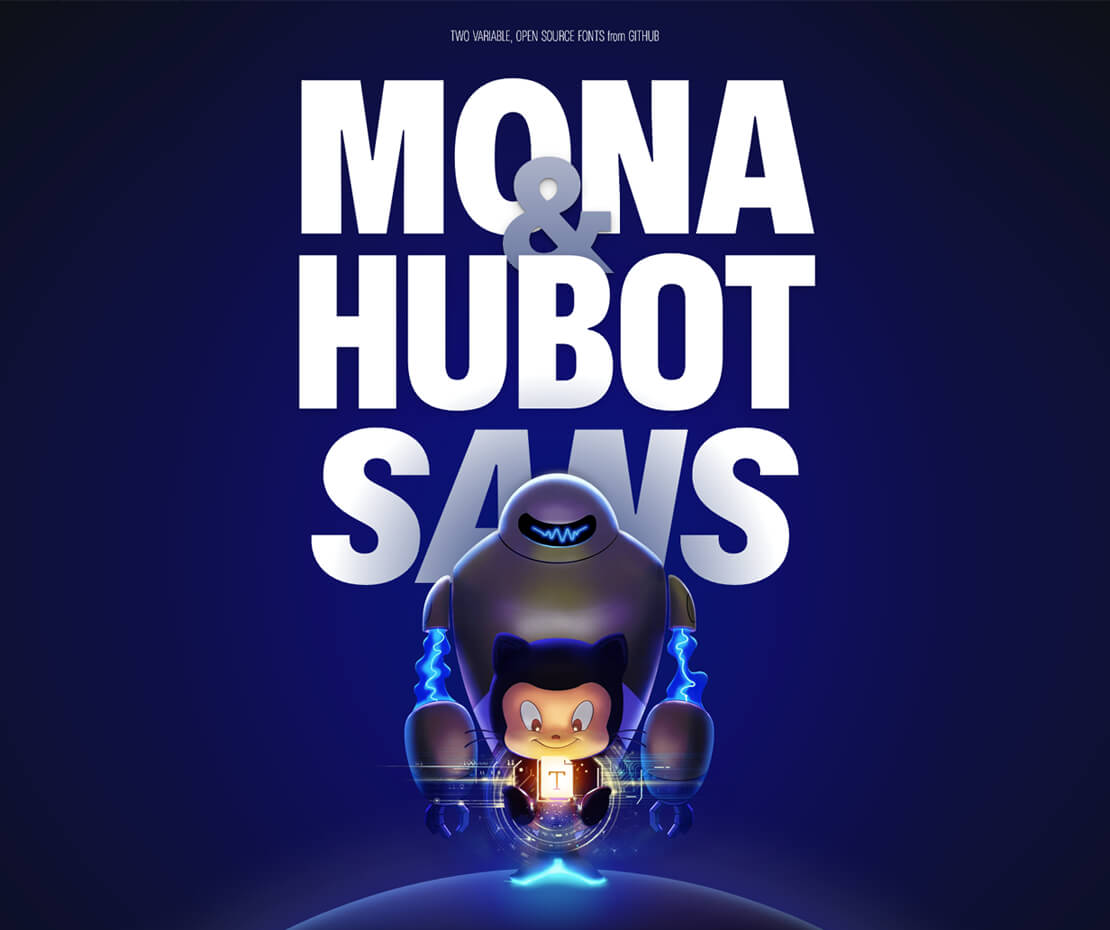
Mona Sans ist als vielseitig verwendbare Schrift konzipiert und sich beispielsweise für Produktgestaltungen oder Darstellung im Web eignet. Die Gestaltung der Buchstaben bzw. ihre Formen erinnern an klassische Groteskschriftarten.
Als »robotischen« Begleiter hat sie Hubot Sans an die Seite gestellt bekommen. Bei dieser Schrift sind geometrischen Aspekte ausgeprägter, was sie entsprechend für Headlines, Zitate etc. prädestiniert.